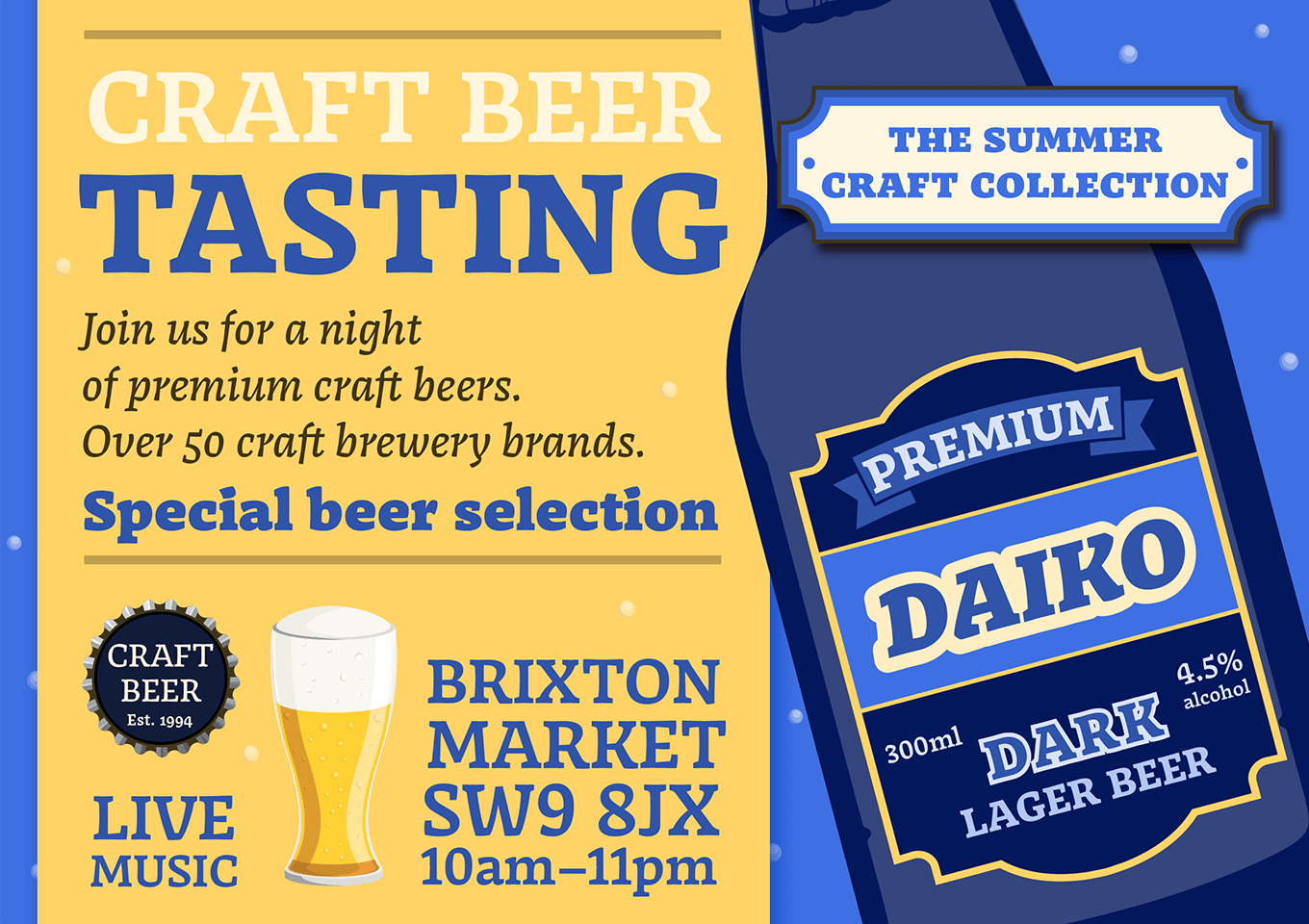
モリサワタイプデザインコンペティション2016欧文部門でモリサワ賞金賞・明石賞を同時受賞した、現代的な本文用セリフ書体です。カリグラフィックな骨格に柔らかさと鋭さが混在するユニークなエレメントを採用したオリジナリティ溢れるデザインながら、抑揚をおさえ、丁寧なカウンターの設計を行っているため小級数や低解像度のディスプレイ環境でも本文書体としての見やすさを失わない点が特徴です。